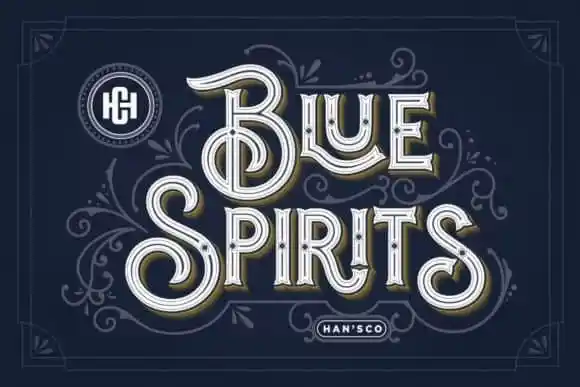
A Blue Spirits Display Font é uma escolha perfeita para designers buscando um estilo vintage com formas limpas e elegantes. Inspirada por HansCo, a fonte traz um toque antigo que se mistura com seu design limpo e moderno. Suas alternativas de caracteres e ligaturas extra permitem que você personalize suas criações de maneira simples e fluida. A Blue Spirits Display é uma excelente escolha para estilos como headlines, logotipos, rótulos, etiquetas e até mesmo material de loja ou assinatura de loja. Seja para criar um design de logomarca atraente ou desenvolver um flyer com o máximo de impacto visual, essa fonte é uma excelente opção. Suas formas geométricas e os traços suaves combinam perfeitamente para trazer um toque nostálgico à sua próxima criação. Com apenas alguns cliques, você pode transformar qualquer projeto em um verdadeiro hit visual.